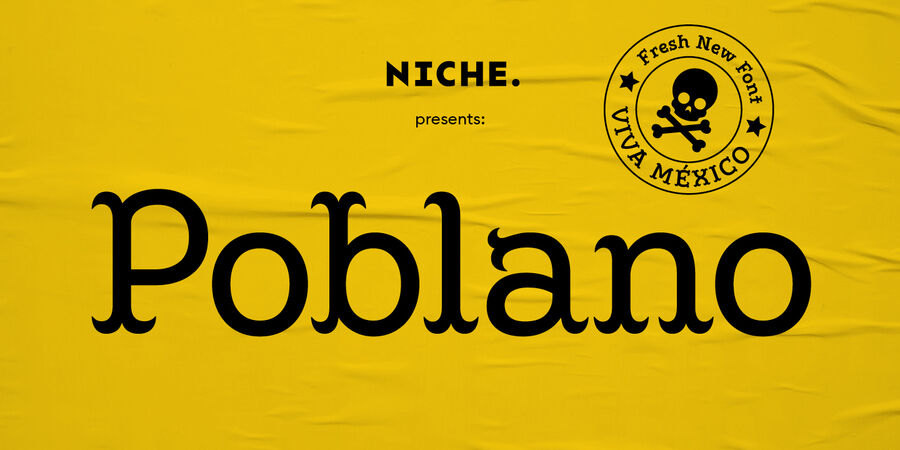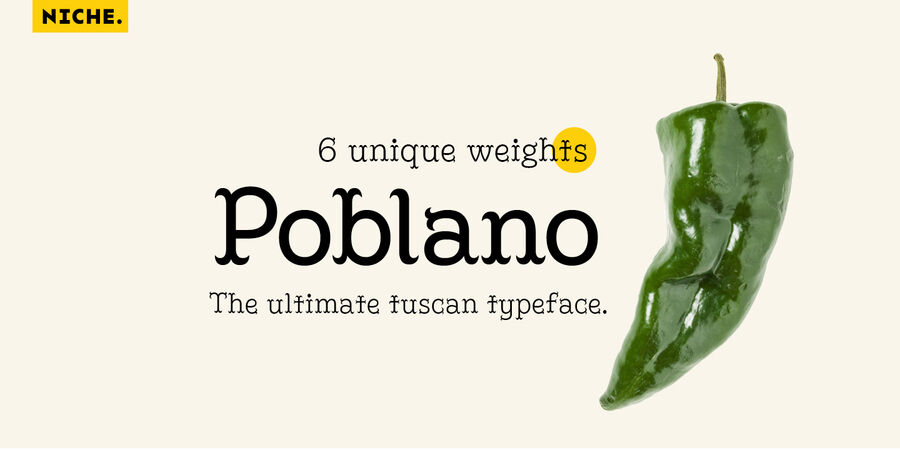
Опис гарнітури PoblanoPoblano – це майстерно зроблена ґарнітура з розкльошеними штрихами, натхненна італійськими ґротесками, які поєднують в собі сучасну веселість і класичну південно-західну вигадливість. З зарубками, схожими на красивий, природний вигин перцю Поблано, цей шрифт відображає суть перцю та ідеальної кількості гостроти й тепла. Найкращий для меню, заголовків і логотипів, Poblano стане незрівнянним гарніром для доповнення та вдосконалення ваших страв – рустикального, гранжевого, хіпстерського дизайну. У меню Poblano входить: насиченості від елегантного тонкого до хвалькуватого наджирного; понад 400 ґліфів на кожне накреслення; понад 50 стилістичних альтернатив; великі та рядкові літери, оригінально стилізовані, щоб додати унікальності вашому дизайну. Це ідеальне рішення для акцидентного і текстового застосування у нішевих проектах. Шрифт розробив Саймон Данфорд у 2019 році.
Асоціації з сімейством шрифтів PoblanoОсобистість і характер гарнітури:
сухий, макабричний, тонкий, легкий, дротяний, осінній, хіпстерський, рукотворний, ручний, натуральний, природний, гнучкий, характерний, круглий, крафтовий, якісний, оригінальний, рослинний, гострий, цікавий, манірний, химерний, чудний, старовинний, колючий, дикий, перчений, неформальний, легковажний, ремісничий, артізанальний, кустарний, дивний, живий, органічний, творчий, екзотичний, іронічний, самобутній, артистичний, південний, кріповий, худий, весняний, екологічний, зелений, ламповий, здоровий, модний, грайливий, потішний, прикольний, свіжий, акуратний, домашній, симпатичний, майстерний, художній, веселий, звіриний, старомодний, фермерський, смачний, гарячий, апетитний, бадьорий, святковий, стиглий, літній, ефектний, добірний, дорогий, яскравий, виразний, пластичний, мультяшний, ковбойський, задерикуватий, добродушний, гулящий, пещений, дотепний, стійкий, спекотливий, спекотний, дерев'яний, пивний, тропічний, запальний, соковитий, щедрий, помітний, сильний, екстравагантний, циганський, демонстративний, претензійний, активний, переконливий, важкий, пузатий, товстий